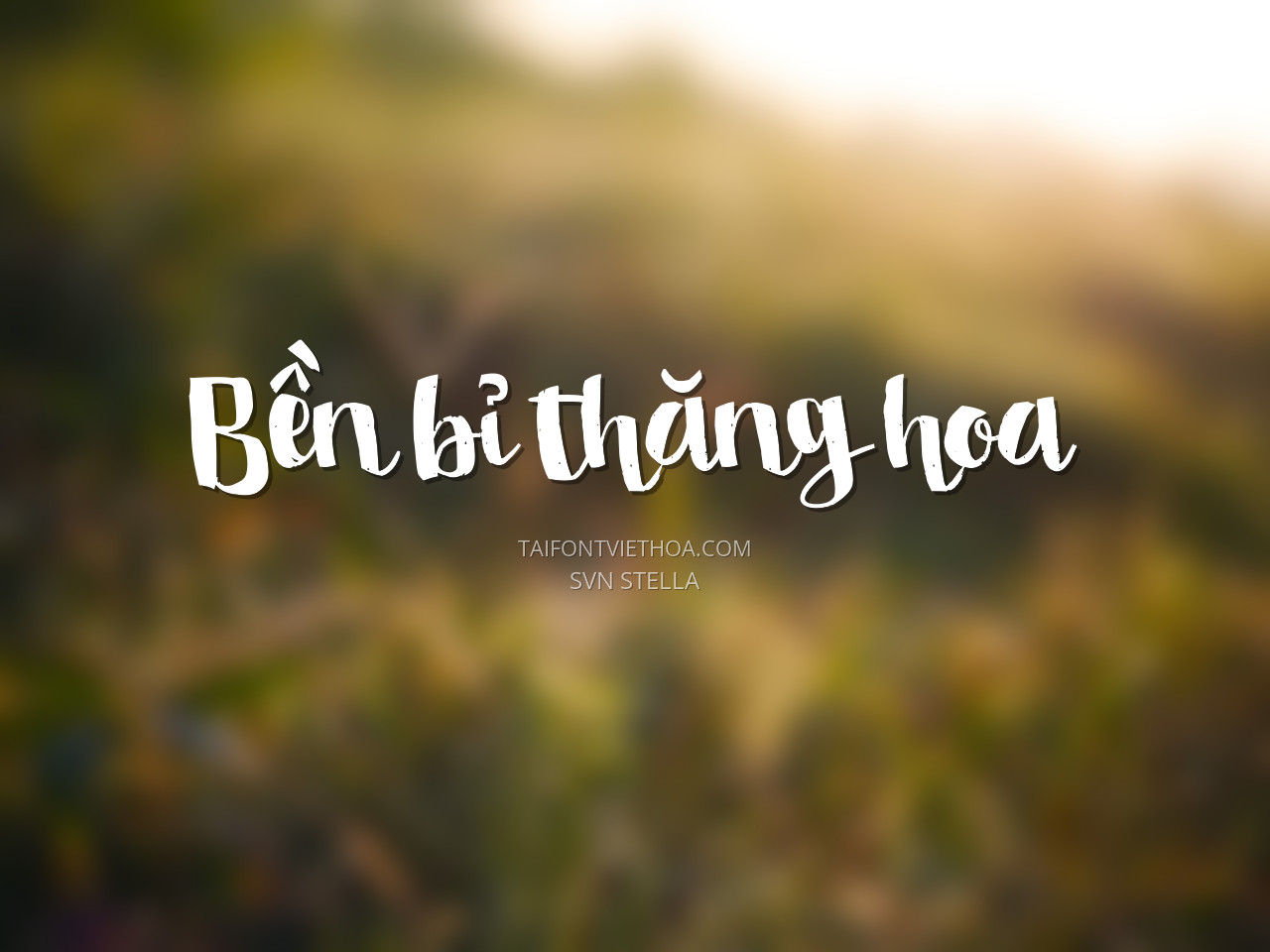
Giới thiệu về Stella – Font script mềm mại, thanh lịch và đầy nữ tính
Stella (tên gốc: Stella Typeface) là phông chữ script mang phong cách viết tay hiện đại, được thiết kế bởi Letterhend Studio(Indonesia) và phát hành trên Creative Market từ năm 2018. Stella lấy cảm hứng từ các đường nét bút máy mềm mại, bay bổng, mang đến cảm giác nhẹ nhàng, duyên dáng mà không kém phần nổi bật cho bất kỳ thiết kế nào. Bản quốc tế hỗ trợ hơn 60 ngôn ngữ Latincùng bộ glyph mở rộng, alternates, ligature và swash trang trí giúp cá nhân hóa từng dự án sáng tạo một cách linh hoạt, ấn tượng.
Phiên bản SVN Stellađã được STYLEno.1 FontsViệt hóa đầy đủ, bổ sung dấu tiếng Việt, chuẩn hóa kerning và tối ưu hóa hinting để hiển thị sắc nét, mượt mà trên cả màn hình lẫn in ấn. Đội ngũ taifontviethoa.comđã kiểm thử thực tế trên Photoshop, Illustrator, Canva…, đảm bảo font không lỗi dấu, không vỡ nét ở bất kỳ kích thước nào. Nhờ vậy, Stella Việt hóa sẵn sàng phục vụ mọi dự án sáng tạo cần sự mềm mại, nữ tính nhưng vẫn chuyên nghiệp và dễ ứng dụng trong thực tế.
Đặc điểm thiết kế, ứng dụng và ngành nghề phù hợp
Stella thuộc nhóm script viết tay, nổi bật với các đường cong nhẹ nhàng, nhịp điệu uyển chuyển và baseline biến thiên giúp chữ cái luôn tràn đầy sức sống. Các alternates, ligature và swash trang trí đa dạng cho phép designer sáng tạo không giới hạn khi trình bày tiêu đề, logo, thiệp mời, hoặc bất kỳ ấn phẩm nghệ thuật nào cần tạo điểm nhấn tinh tế, sang trọng. Stella còn phát huy hiệu quả khi kết hợp cùng font sans-serif hiện đại hoặc serif cổ điển, giúp tổng thể thiết kế cân bằng và nổi bật.
Ứng dụng tiêu biểu
– Logo & nhận diện:Spa, beauty salon, shop thời trang nữ, wedding planner, studio ảnh cưới.
– Ấn phẩm nghệ thuật:Thiệp cưới, poster sự kiện, story social media, banner quảng cáo, sổ tay sáng tạo.
– Bao bì & nhãn mác:Mỹ phẩm handmade, sản phẩm thủ công, hộp quà, sticker, thiệp cảm ơn.
Ngành nghề phù hợp